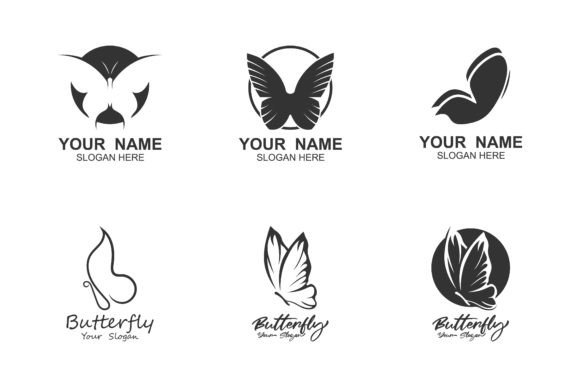
Butterfly Logo
การค้นหาองค์ประกอบการออกแบบที่เหมาะสมอาจเป็นเรื่องท้าทาย แต่ Butterfly Logo นำเสนอคอลเลกชันที่โดดเด่นซึ่งช่วยยกระดับงานของคุณได้ทันที
ไม่ว่าคุณจะสร้างผลิตภัณฑ์ POD (Print on Demand) คำเชิญงานแต่งงาน หรือกราฟิกโซเชียลมีเดีย Butterfly Logo ก็เหมาะสมอย่างยิ่ง